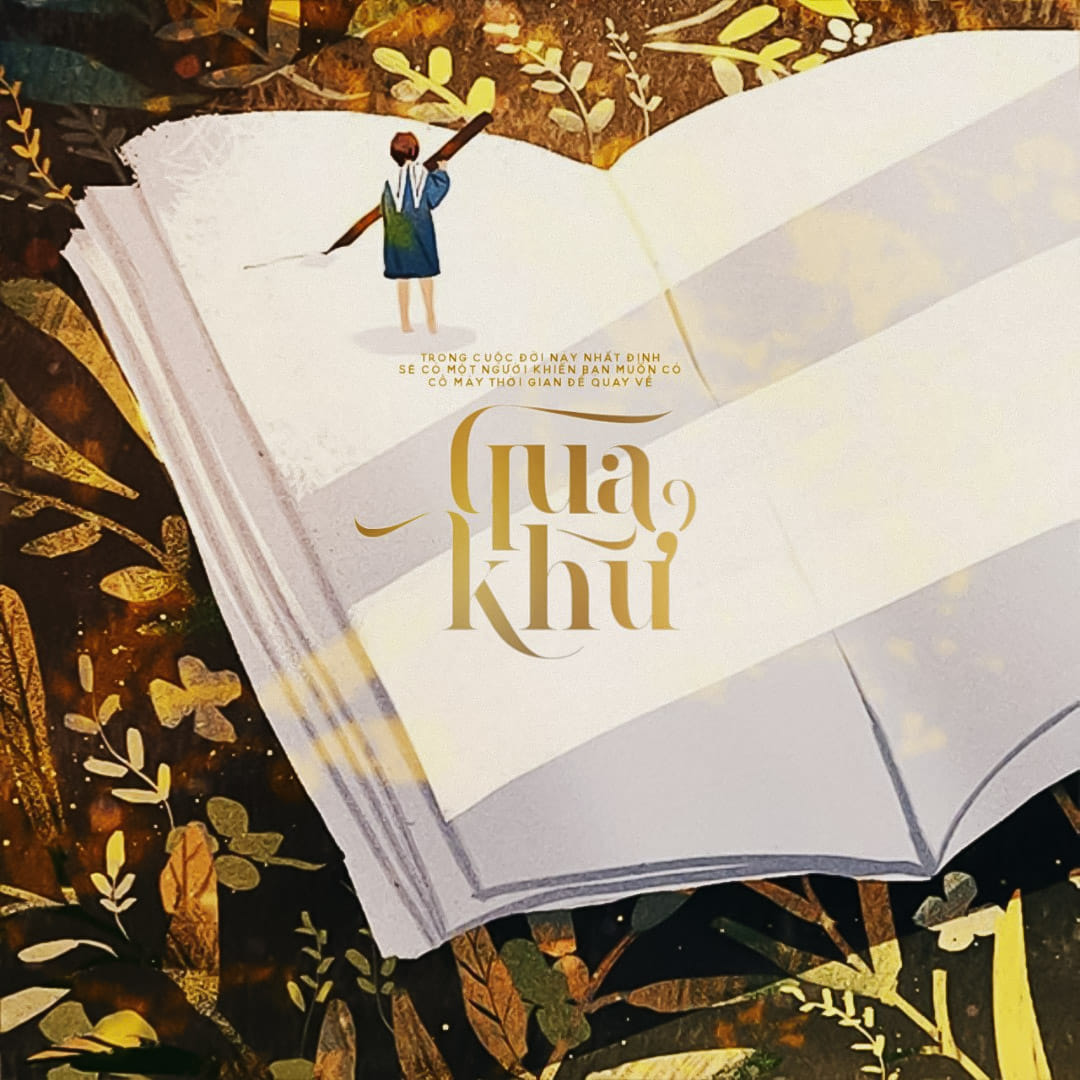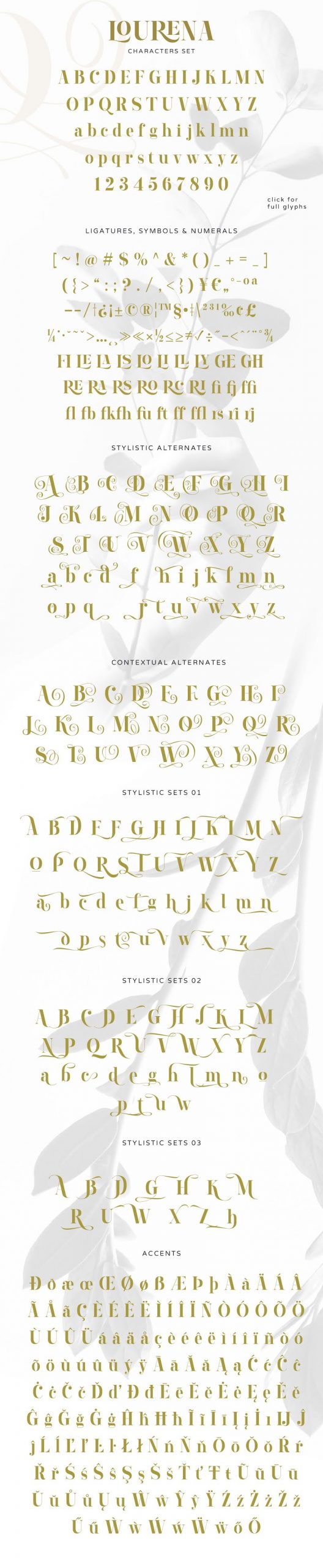
[Serif] Tải font Lourena Việt Hóa miễn phí
Lourena Việt Hóa, font chữ serif thời trang với nhiều tính năng bổ sung. Một bộ font chữ thanh lịch lấy cảm hứng từ đồ họa và thư pháp trang nhã mà bạn có thể sử dụng trên nhiều thiết kế.
Font chữ này được thiết kế với vẻ ngoài sang trọng, hiện đại và tối giản, rất tốt cho việc sử dụng biên tập, cũng trông hoàn hảo để kết hợp trong các font chữ viết tay hoặc chữ ký.